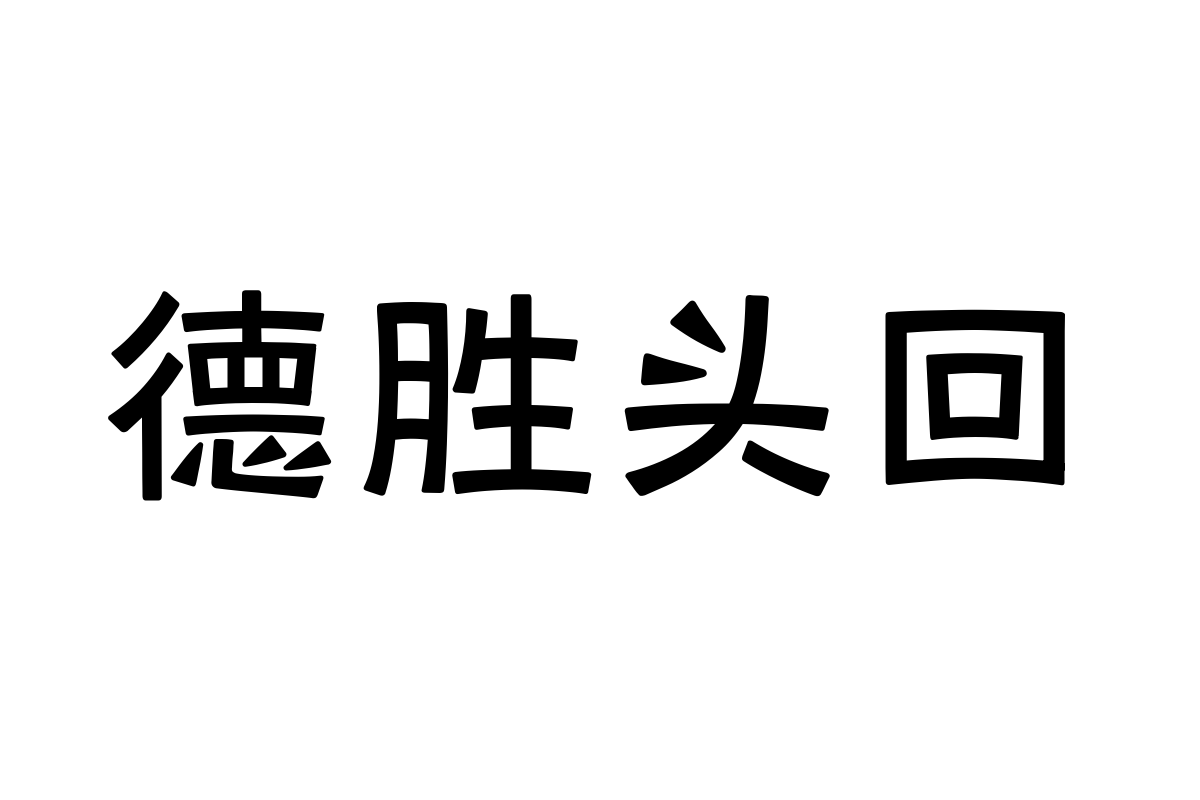
汉仪碑刻黑是一套由汉仪公司设计的中文字体,主要用于书法和艺术设计。这套字体的特点如下:
1. 字形优美:汉仪碑刻黑的字形结构独特,线条流畅,给人一种优雅、古朴的感觉。
2. 笔画细腻:这套字体的笔画精细,每一个细节都经过精心设计,使得书写时手感良好,易于掌握。
3. 风格独特:汉仪碑刻黑的字体风格独特,既有传统的韵味,又不失现代感,适合用于各种场合的书法和设计。
4. 适用范围广泛:这套字体适用于书法、广告、包装、报纸、杂志等各种设计领域,具有很强的实用性。
总之,汉仪碑刻黑是一款非常优秀的中文书法字体,适合用于各类设计项目。